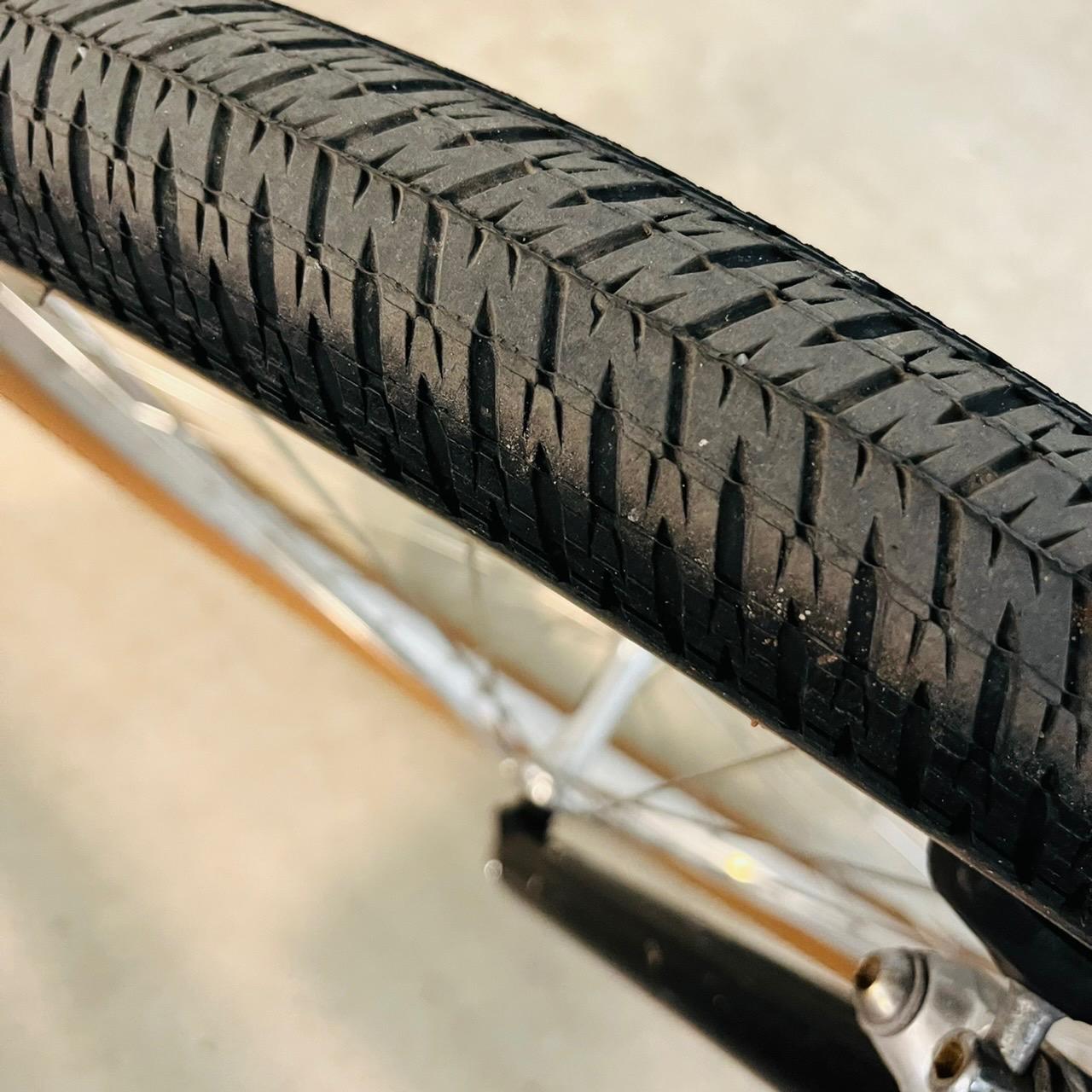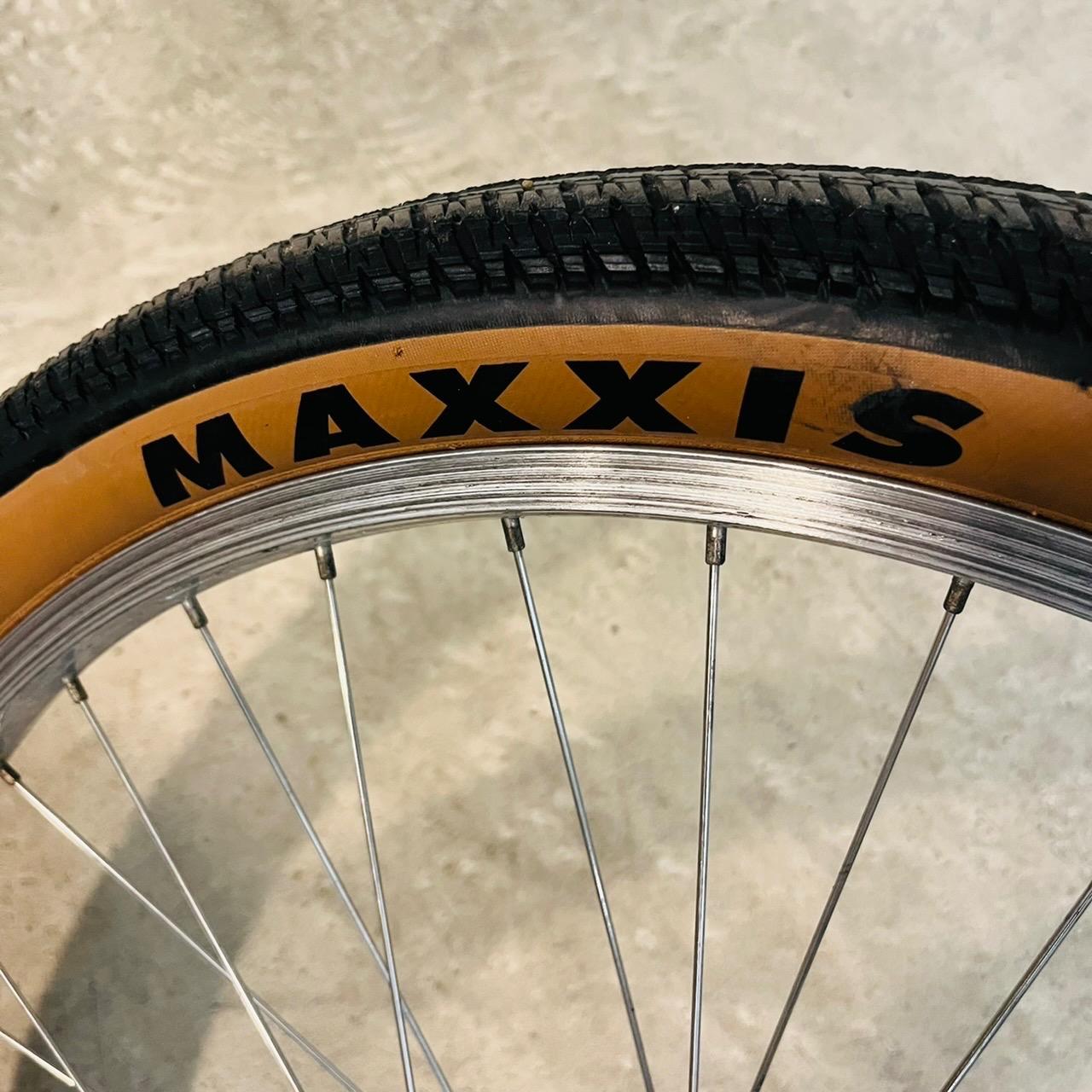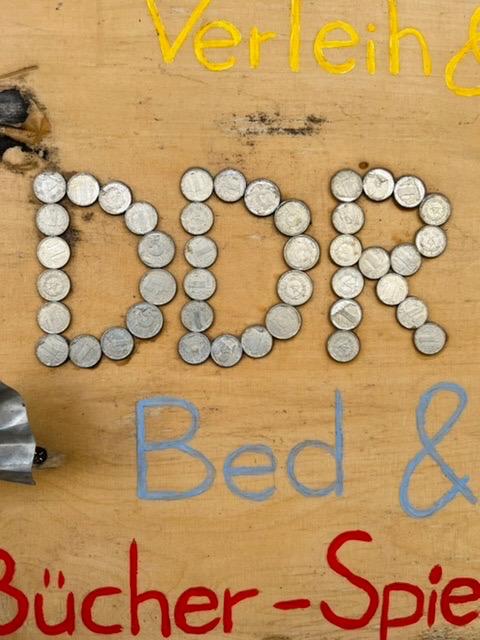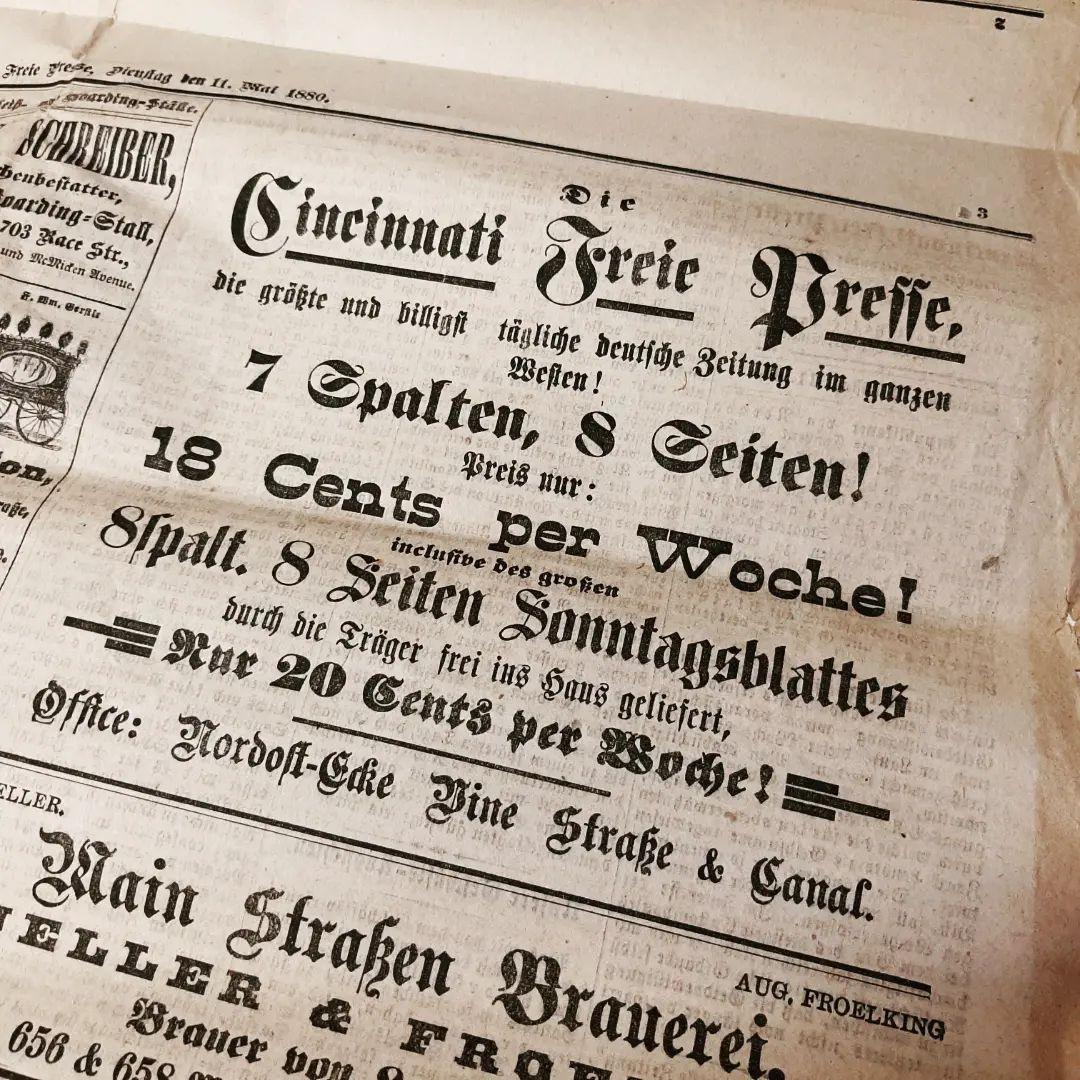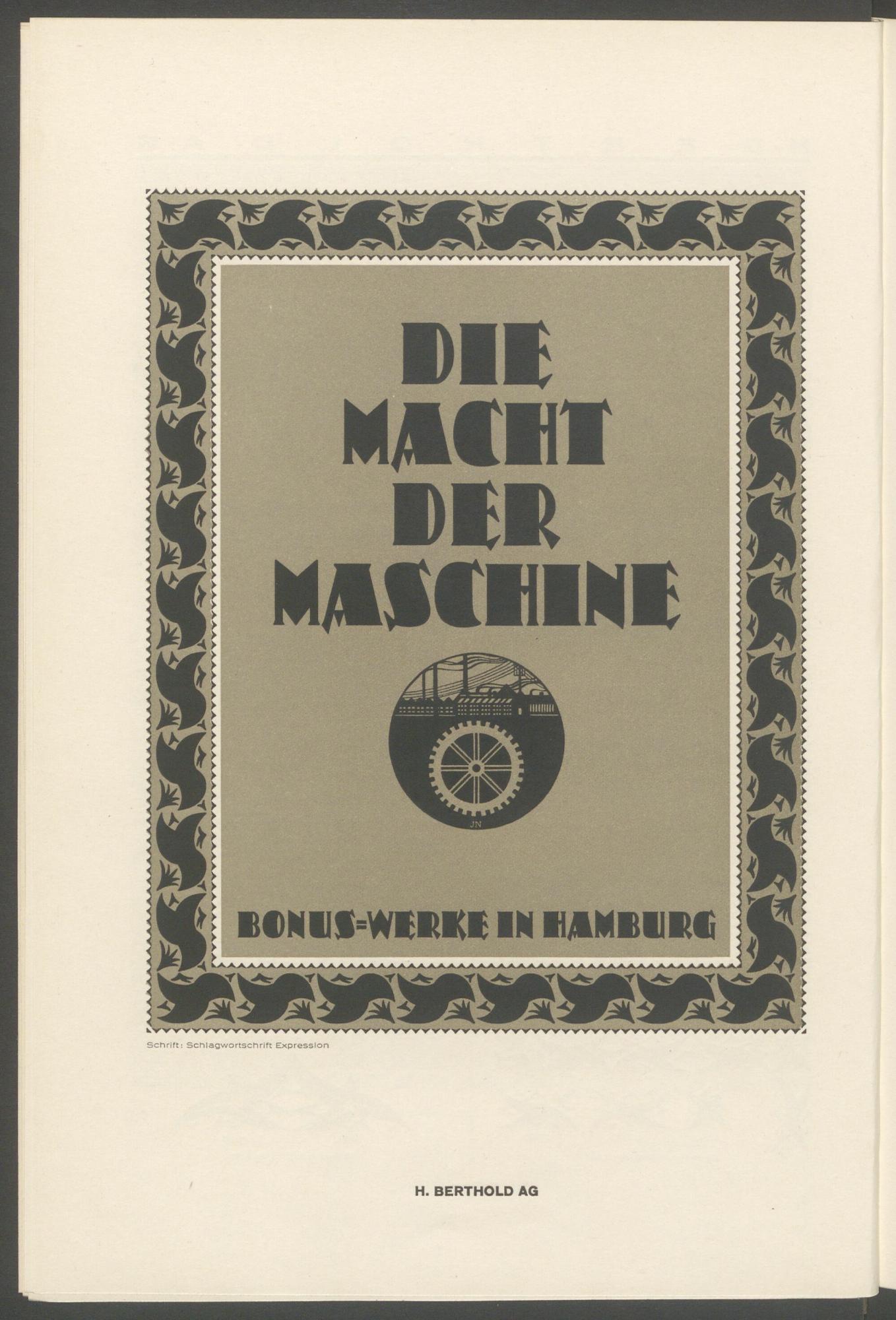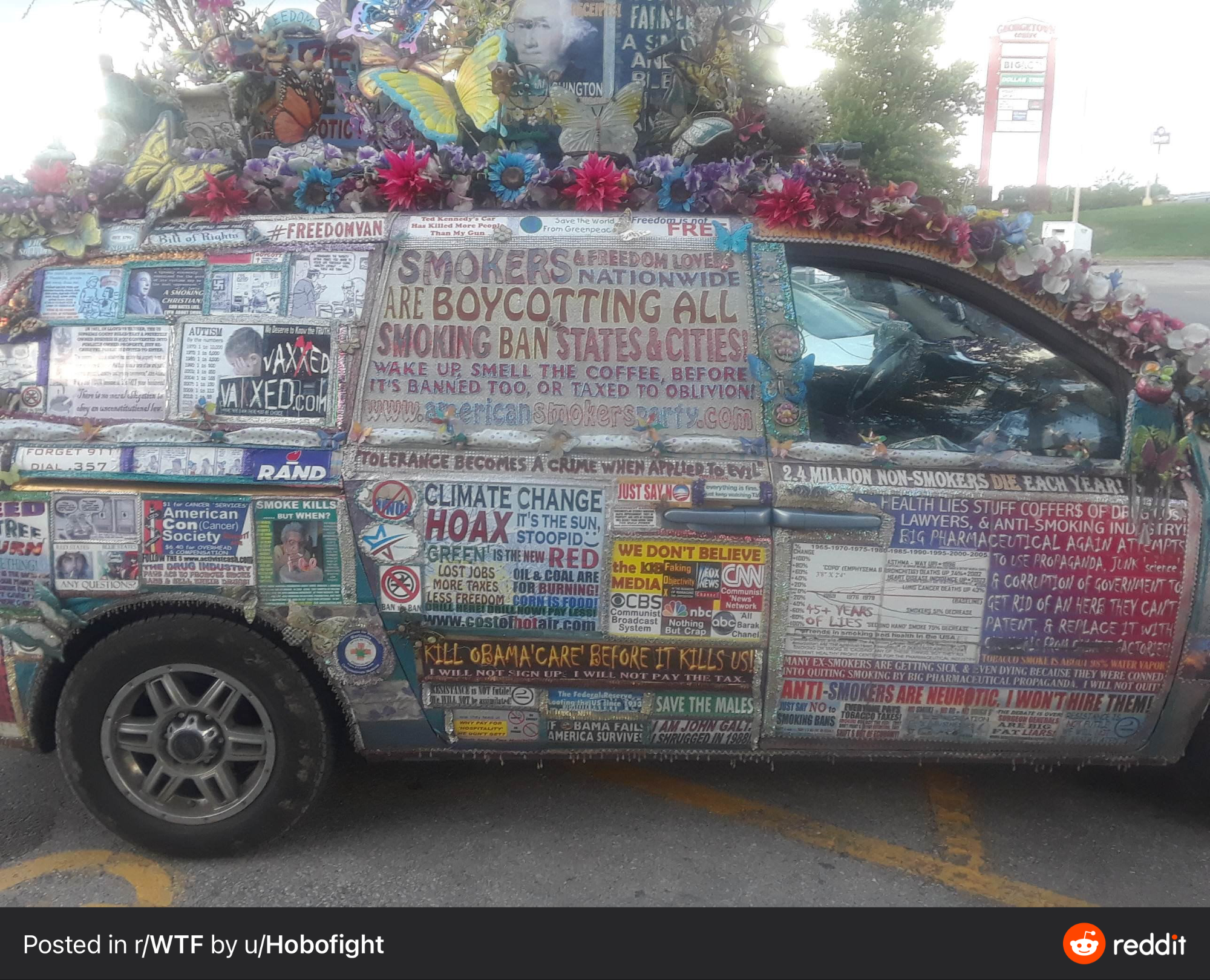
Heute bei Instagram gefunden. Eine Anzeige aus der "Cincinnati Freie Presse" von 1880. Vor dem ersten Weltkrieg gab es über 300 deutschsprachige Zeitungen in den USA. Interessante Mischung nicht nur von Deutsch und Englisch, sondern auch von Fraktur und Antiqua,
Ästhetisch sehr ansprechend die Schrift zusammen mit der restlichen Grafik. Schade nur, dass es ein Custom Font ist.
Soll irgendwann veröffentlicht werden. Das Recht hat sich Tosha Omagari gesichert:
they kindly allowed me to publish it in the future.
Ich bin besonders auf den kyrillischen Teil gespannt!
Ein Quiz! Hobo und Blair habe ich schon mal entdeckt!
Copperplate Gothic (Climate Change), Futura, Berlin Sans FB, Chiller (Obama Care). Bank Gothic (Forget 911 Dial .357) ... Cooper Black (Ted K.s Car) ...
Ist aber auch irgendwie hipstergroteskig, oder :-?
Ich finde sie sehr viel origineller und charmanter als das Gros der Hipster Grotesken (die ich oft nicht auseinanderhalten kann) ...
Die ist halt auch nicht schwarz/weiß dargestellt.
Das sind doch aber die wenigsten ...
Meinst Du?
Alles schwarz-weiße Hipster-Foundries. 🤷🏼‍♂️